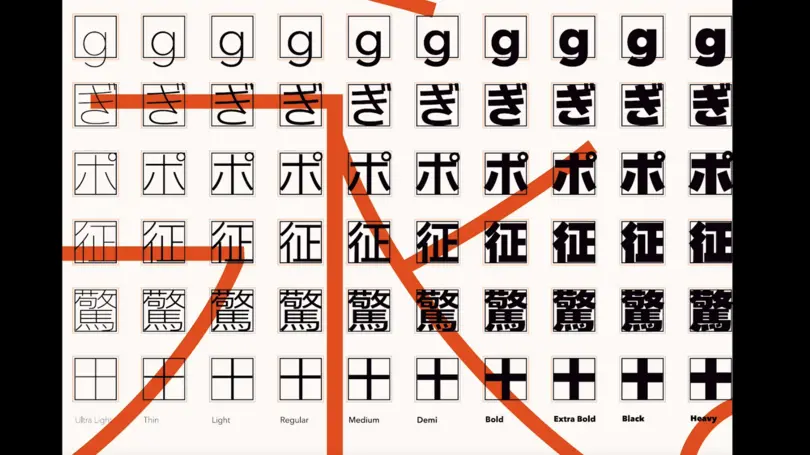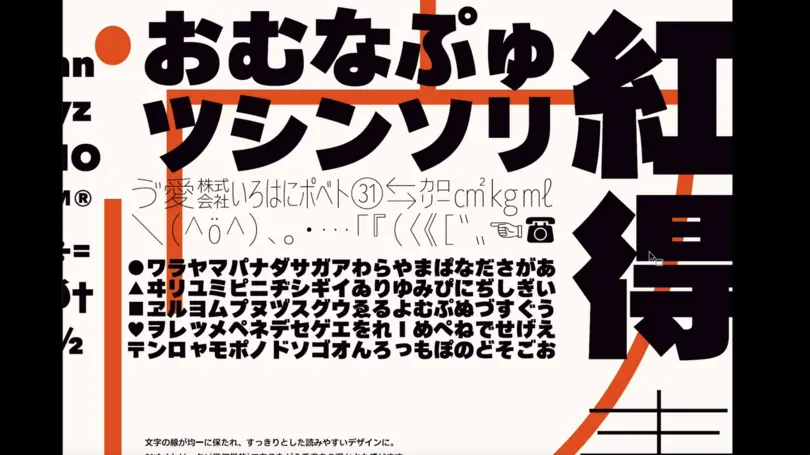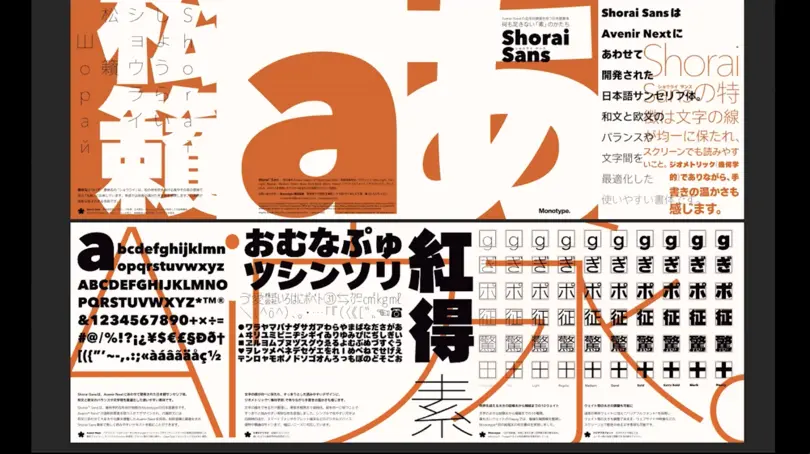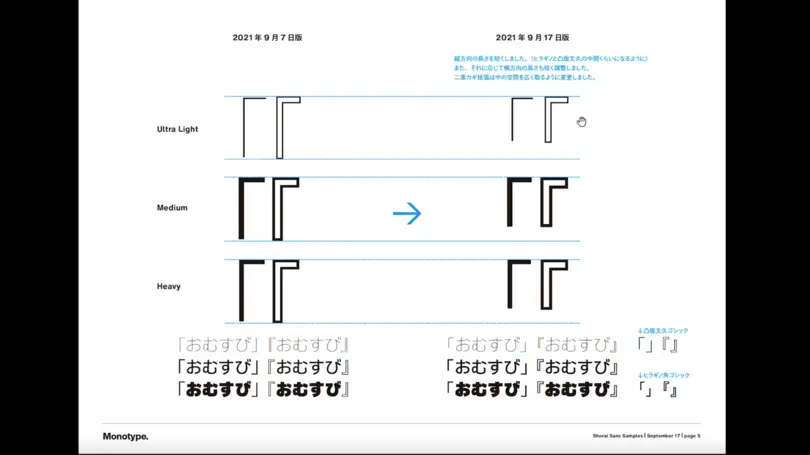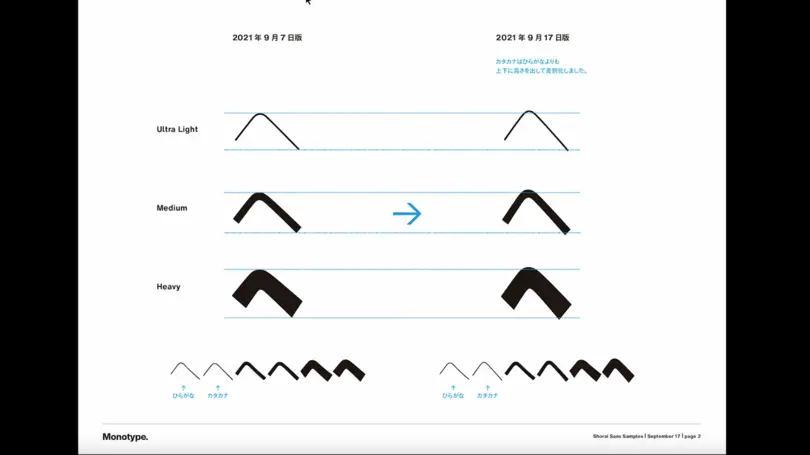
Shorai Sans 見本帳制作の裏側
Shorai Sans の見本張デザインを担当したコズフィッシュ代表の祖父江慎氏をお招きしトークセッションを行いました。
2022年2月にリリースされた Monotype の和文書体 Shorai Sans。Avenir Next にあわせて開発された、すっきりと読みやすい和文書体です。書体の発売を記念して、オンラインのトークイベントが開催されました。
このトークイベントでは、書体制作にかかわった Monotype クリエイティブ・タイプディレクターの小林章、Monotype シニア・タイプデザイナーの土井遼太が登壇。ゲストスピーカーとして、Shorai Sans の見本帳デザインを担当した祖父江慎氏、Shorai Sans の書体デザインに携わった中村征宏氏を迎えて、2つのセッショントークが行われました。
見本帳のデザインを依頼した経緯
Session 1では、Shorai Sans の書体見本帳をデザインした祖父江慎氏が登場。祖父江氏は小林が執筆した書籍『フォントのふしぎ』『まちモジ』のデザインも担当しており、氏の文字に対する愛情やわかりやすく伝えようとする姿勢に小林は注目していたと言います。Shorai Sans の見本帳を制作するにあたり、小林は書体の魅力を伝えてほしいと考え、祖父江氏にデザインを依頼しました。
文字についてなら何時間でも語れるほど、文字好きな祖父江氏。見本帳のデザインを打診された時も、どんな書体なのか、とても楽しみだったと言います。Monotype と最初に打ち合わせをするまで、書体の概要や中村征宏氏の参加は知らされていなかったので、詳細を聞いて驚いたそう。
極太文字をどう作るか
Shorai Sans の制作で最も頭を悩ませたのは、Avenir Next Heavy の太さにあわせた和文の極太文字をどう作るかでした。特に漢字は画数が多いため、そのまま極太にすると線がぶつかって読めなくなってしまいます。小林は中村氏が作ったゴシック体のゴナに注目。最も太いウェイトのゴナUでは、不可能と言われた超極太文字が見事に書体化されており、極太書体を作るなら中村氏の力を借りたいと考えました。
例えば、漢字の「十」は、かなり重心が高く作られているので、普通は威張って感じられるが、キュートになるのは中村氏のバランス感覚のためではないか、と祖父江氏は分析。「得」のぎょうにんべんでは、線の重なり方が絶妙で、おおらかさと強さに驚いたと言います。
ひらがなの「き」では、細いウェイトでは3画目がつながっているのに対し、Extra Bold  以降の太いウェイトでは分離。太いウェイトで3画目をつなげてしまうと文字全体の密度が増してしまうため、途中で切り離しています。
Shorai Sans では線をなるべく単純にして複雑に見えないようにした、と小林。太いウェイトでは、ぎょうにんべんの1画目と2画目をくっつけることにより、一つのまとまった形に。一方、3画目(縦棒)の始筆部の右上が2画目とつかないようにして軽さを表現。太さと軽さのバランスをとりました。
見本帳に入れた文字
見本帳では画数の多い文字と少ない文字を見せたかった、と祖父江氏。画数の少ない「十」の上に画数の多い「驚」を置き、比較して見せています。ひらがなは、Shorai Sans の特徴が最も出ている「お、む、な、ぷ、ゅ」を掲載。その下にカタカナの読み間違えやすい文字「ツ、シ、ン、ソ、リ」を選択。
また、Monotype の和文書体は、欧文書体にあわせてデザインされているため、和文と欧文のサイズや位置が調和するようにあらかじめ設定されているのも特徴です。フォントをそのまま打つだけで、自然な和欧混植が可能になります。通常の和文書体では、和文書体にあわせて欧文書体を作りますが、Monotype では欧文にあわせて和文を作るところが画期的、と小林は言います。
見本帳全体のデザイン
「見本帳を作るときに注意したのは、それが物質であるという点です」と祖父江氏。印刷された状態で物質としてどう見えるかを考慮し、少しクリームがかった紙を選択。鮮やかすぎずに発色のよい色ということで、キーカラーを朱色に。見本帳の外側の紙面では朱色部分に、内側の紙面には黒い文字のところにニスを乗せ、存在感を出したそうです。
見本帳の表紙には、ひらがなの「あ」をはみ出すように入れ、表紙をめくったところに10ウェイトの見本を掲載。大きな文字には細いウェイト、小さな文字には太いウェイトをあてることにより、文字のサイズが変わっても同じ太さに見える書体見本も作成し、10ウェイトの効果的な活用方法を見せています。
見本帳の裏面には、Shorai Sans の由来となった言葉「松籟」を掲載。松籟とは、松の枝を吹き抜ける風やその音を意味する言葉で、茶道では茶釜の湯がたぎる音を意味すると言われています。たづがね角ゴシックの「たづがね」が鶴を意味していたので、鶴と言えば松ということで、松に関連がある言葉に。音の響きがよく、どの国の人でも発音しやすいことを意識したと言います。
見本帳の内側の紙面には、欧文、ひらがな、カタカナの文字見本を掲載。ひらがなの「お」は、学校で習う「お」の形。「む」は、2画目のくるっと回る部分が下の方にあり、手で書いたように自然な形をしている、と祖父江氏は指摘します。「お、む」の横線は定規で引いたような直線ではなく、手で書いたニュアンスが微妙に残っていて、「お、む」の2文字を見ただけでこの書体のすごさがわかる、と言います。
見本帳制作時に変更された文字
「写植時代まではカギカッコは小カギがメインだったのですが、デジタルフォントになると大カギばかりになりました。小カギにしたい時は入れ替えなければならず、面倒だったんです」と祖父江氏。見本帳を制作する過程で、そのような指摘を受け、Shorai Sans のカギカッコの形を変更。2021年9月7日の時点では、カギカッコが長いままですが、9月17日には祖父江氏の意見を取り入れて短くしています。
ひらがなの「へ」とカタカナの「ヘ」も祖父江氏の意見をもとに調整。9月7日の時点ではひらがなとカタカナの違いがわかりづらかったため、9月17日には、カタカナの高さをひらがなより少し高くし、角度も鋭角にして、より明確に違いがわかるように変更しました。
ひらがなの「へ」は行頭に来ないことが多いのですが、カタカナは「ヘルシンキ」「ベルリン」など単語の頭に来ることがあるため、このような形に。祖父江氏のアドバイスを受けて、単語を組んだ時にしっかり見える形に調整されています。
「書体見本帳の形を最初から決めず、相談しながら作っていきました。遊びの部分をこんなに残せたのもうれしいです。見本帳のデザインでは、デザイナーとして書体を使う時に気になるポイントを盛り込みました」と祖父江氏。
「祖父江さんと書体見本帳を作りながら、書体の文字の形が変わっていくというのも面白い体験でした。見本帳のデザインだけをお願いするのではなく、書体を作る側と使う側でやりとりし、書体を使う側からのご意見をいただいたのがよかったです」という小林の言葉で Session 1 が終了しました。